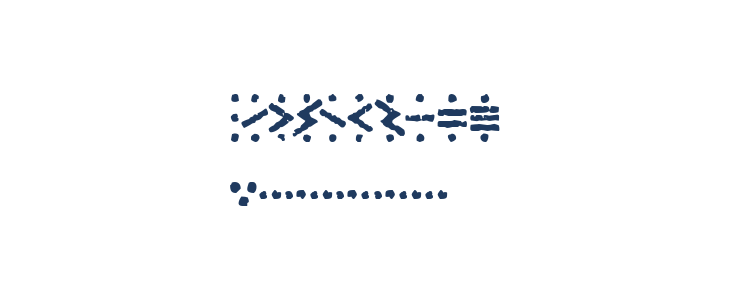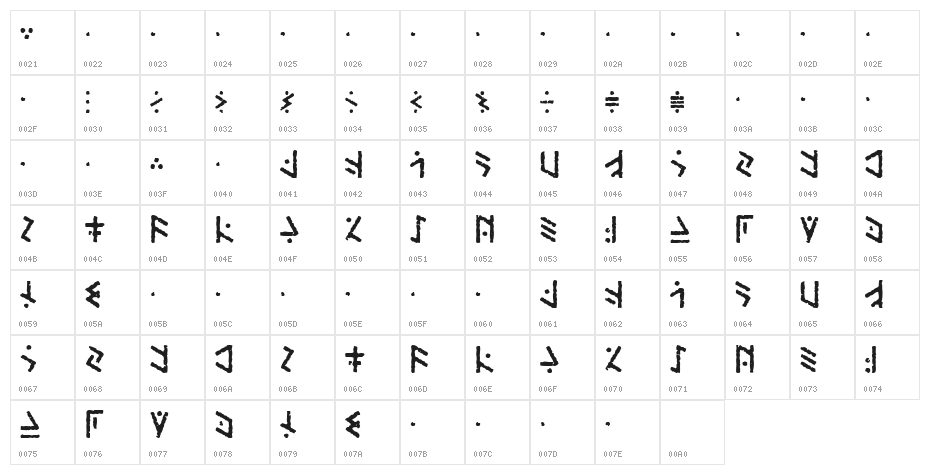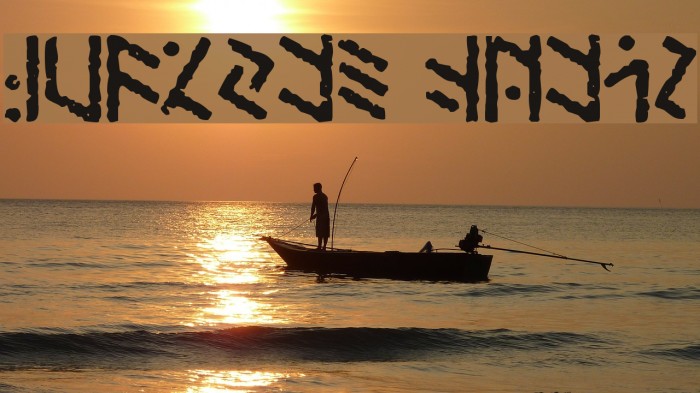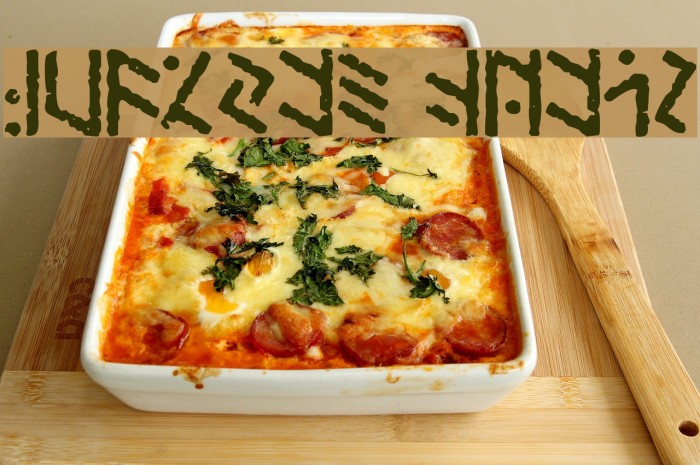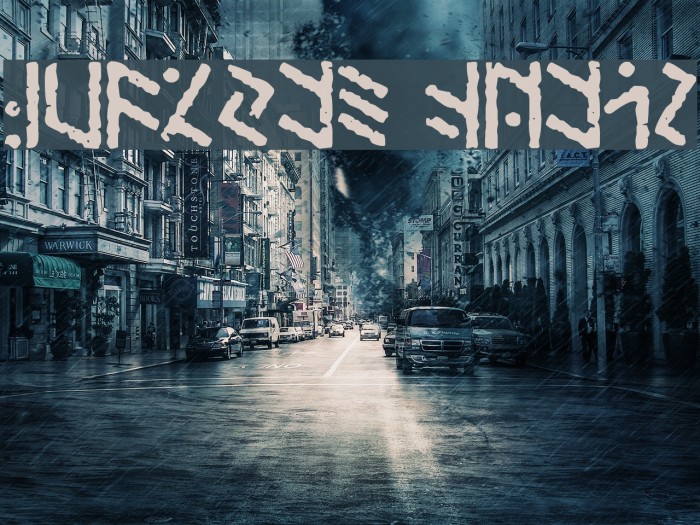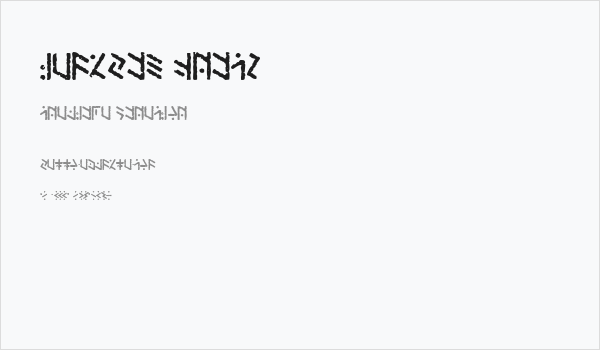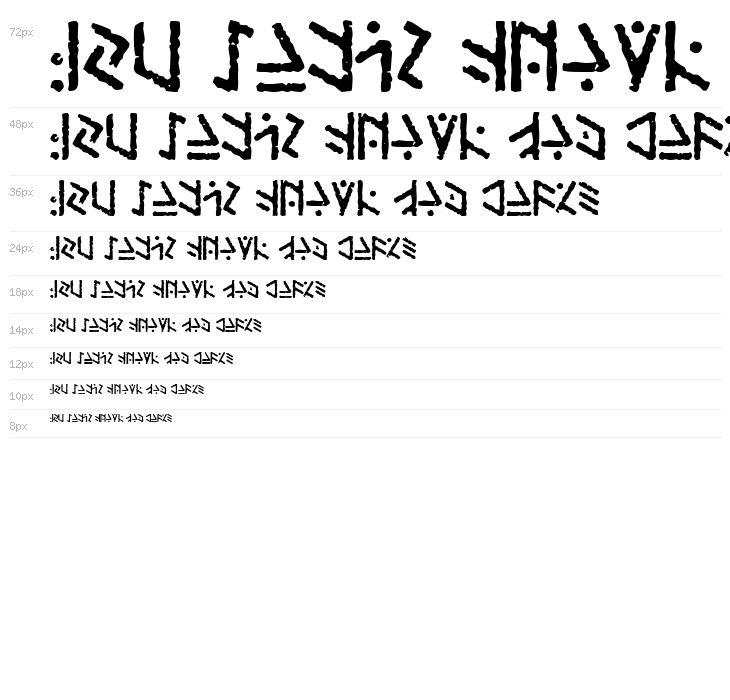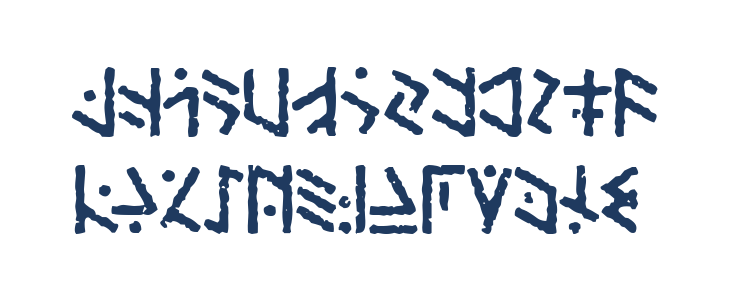
Temphis Brick Font
| Caso d'uso | Artistic projects, fantasy themes, decorative purposes. |
| Progetti proposti | Ideal for fantasy-themed designs, game interfaces, or artistic projects requiring a unique script. |